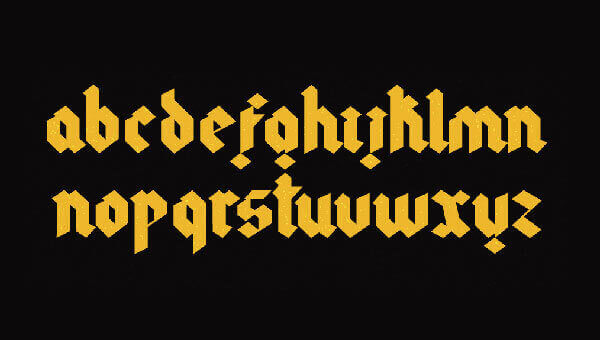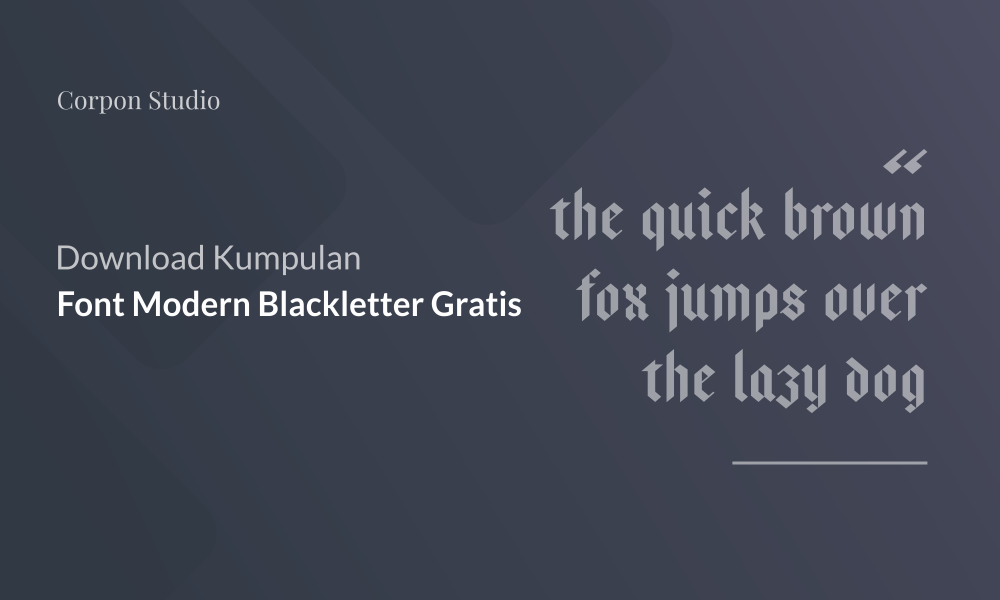
Kumpulan gothic blackletter font yang bisa di download secara gratis
Untuk tipografi, "hand lettering fonts" selalu terlihat lebih menarik dan lebih diminati. Tak heran jika jenis font ini lebih banyak di cari di marketplace. Salah satu yang menarik adalah blackletter font, jenis ini bisa adalah perpaduan antara tipografi dan tulisan tangan yang memberikan arah, makna dan sentuhan baru pada font, sekilas font ini terlihat seperti Sans serif biasa namun juga terlihat seperti buatan tangan yang ditulis dengan pena kaligrafi berujung lebar.
Desain karakter Blackletter dibuat berdasarkan bentuk huruf dari tulisan tangan populer pada abad pertengahan di Jerman (gaya Gothic) dan Irlandia (gaya Celtic). Pada awalnya gaya tulisan ditulis menggunakan pena berujung lebar sehingga menghasilkan kontras tebal tipis yang kuat. Untuk menghemat media, karakter ditulis berhimpitan, sehingga hasil keseluruhan berkesan gelap dan hitam, dari sinilah gaya tulisan ini dinamakan Blackletter.
Ciri awal dari huruf ini adalah memiliki sirip/serif/kaki yang lancip pada bagian ujung, jarak(kerning) antara huruf sangat sempit hingga berkesan Gothic. Kesan yang ditimbulkan adalah klasik, gelap, berat dan hitam.
Pada masa sekarang desainer sudah banyak mengkreasikan jenis font ini hingga menghasilkan Blackletter tanpa sirip/serif/kaki yang juga sering disebut dengan Modern Blackletter. Dalam postingan ini kami akan membagikan beberapa koleksi font modern blackletter, terdapat 10 font yang keseluruhan bisa Anda download secara gratis untuk tipografi atau proyek desain lainnya.
Bajern Free Typeface
Demonletter Modern Blackletter font
Dreifraktur Modern Blackletter Font
Fibonacci Fraktur Free Modern Blackletter Font
Gothic Modern Typeface
Kodex Modern Blackletter Font
ORDNUNG free Display font
Ozymandias Free Parallel Pen Font
Rubia Perfect Parallel Typeface
Santiago Blackletter Free Typeface